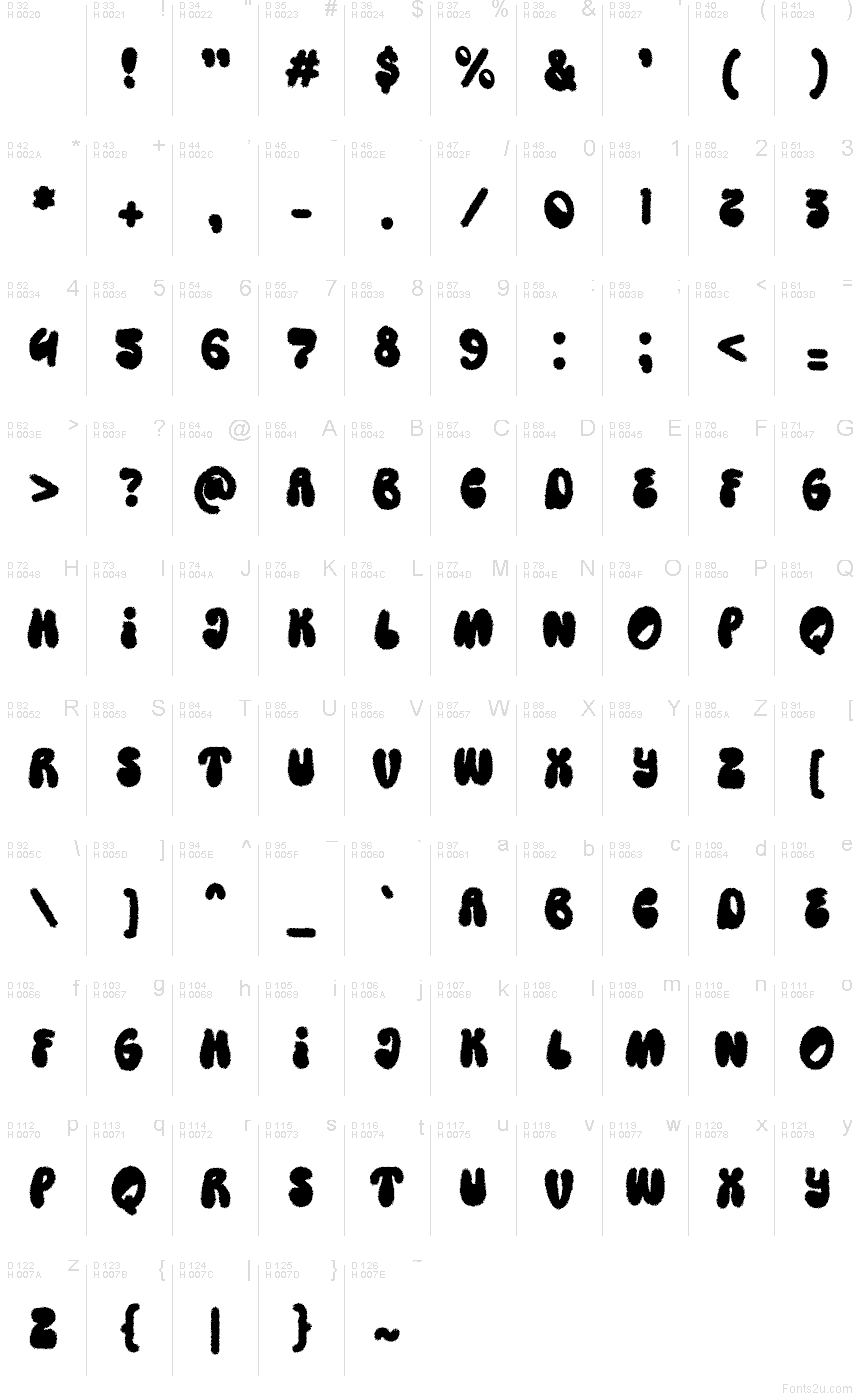
Cinbrows de Yumnacreative es una tipografía de visualización de dibujos animados erosionada y gratuita, con letras hinchadas e irregulares y una silueta viva y cortada a mano. Las curvas suaves mantienen las formas accesibles, mientras que los bordes granulados añaden una textura impresa áspera.
Los gráficos de dibujos animados son su territorio natural, especialmente el entretenimiento infantil y los pósteres de cómics. Las formas sobredimensionadas también se adaptan a los envases de aperitivos y al merchandising divertido, donde el acabado rugoso puede evocar criaturas peludas o tinta desordenada. Para una marca de comida informal, puede convertirse en un logotipo con aspecto de mascota.